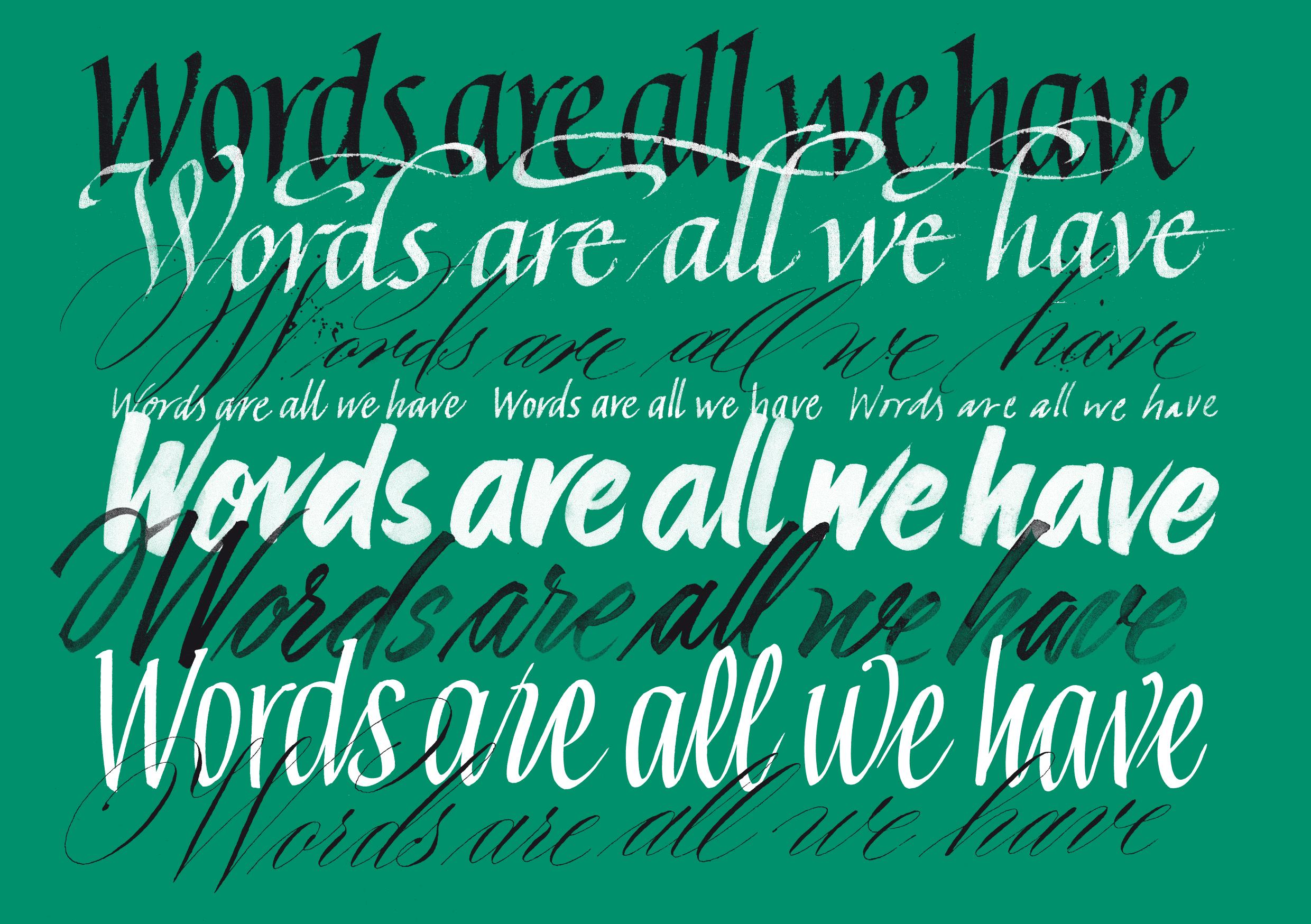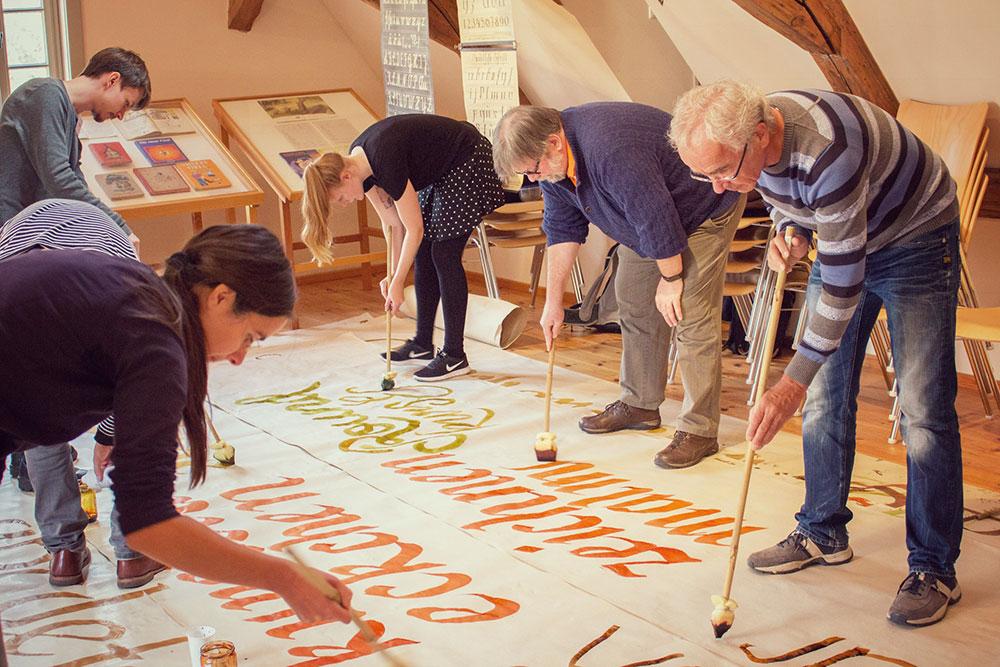
Script-Expeditionen. Von Kalligrafie zu Handlettering
Ohne Wurzeln keine Flügel. Dieser dreiteilige Kalligrafie-Kurs mit Tobias-David Albert in der Pavillon-Presse Weimar baut von sich von einer Renaissance-Kursiven oder Italic über das Schreiben von englischer Schreibschrift bis hin zu amerikanischen Brushscript-Schriften auf. Alle drei Kurse sind so angelegt, dass sie auch ohne die Teilnahme an den anderen beiden möglich sind. Es macht aber mehr Freude, schon etwas Erfahrung zum vorhergehenden Thema mitzubringen. Jeder Teil findet an einem Wochenende in der Pavillon-Presse Weimar statt. Die Anmeldephase für Teil 1 ist jetzt eröffnet.
Beschreibung: Am ersten Kurswochenende arbeiten wir mit Breitfedern aus Bambus und Gänsekielen, Paralell Pen und Ruling Pen (Ziehfedern) hin zu großen Schreibschwämmen in großen und ganz kleinen Schriftgrößen. Es gibt Beratung zu Schreibgerät, Schreibflüssigkeit und Schreibpapieren, sowie interessante Literatur und Vorlagen. Die Kursive ist die Mutter der Handschrift und bildet die Basis für lebendiges Schreiben zwischen Tradition und Moderne.